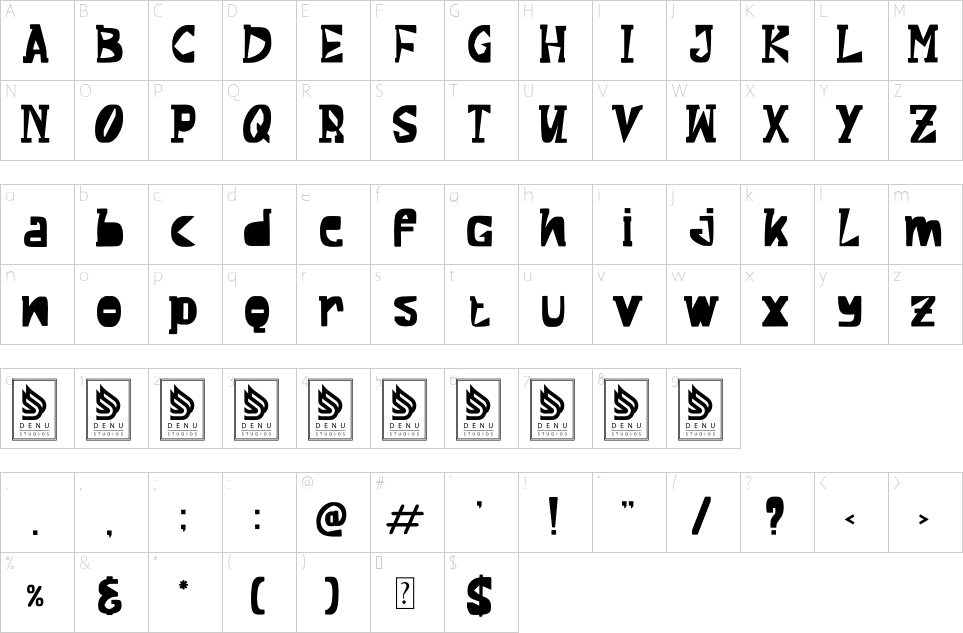
A fonte Munch Mallow é um charmoso adorno para seus designs digitais, projetada pelo designer desconhecido da Gracetypestudio. Se você é um fã de fontes que combinam um toque de modernidade com uma pitada de delicadeza, essa é a fonte para você. Com um design que capta o melhor dos traços de uma fonte cálida e familiar, Munch Mallow é perfeita para nomes de empresas, design gráfico, ou até mesmo para aqueles trabalhos de escritório onde um toque delicado pode transformar a experiência de leitura. Para os designers que buscam uma fonte que combine a facilidade de uso com uma aparência estilosa, Munch Mallow é uma excelente escolha. Seu design arredondado e elegante faz com que seja muito confortável para usar em textos de grande e pequeno tamanho. Não importa se você está fazendo um logotipo inspirado no bebê Munch de “A Pequena Sereia”, criando uma linha de produtos ou apenas redigindo um projeto de escritório, a Munch Mallow estará sempre pronta para dar um toque de criatividade à sua obra. O que mais nos encanta sobre a Munch Mallow é o fato de ser uma fonte gratuita, disponível para Windows e Mac. Isso significa que você pode experimentar o design da fonte sem gastar nada adicional. Com mais de 130 downloads, é evidente que muitos designers já encontraram valor na Munch Mallow e a usaram para expressar sua identidade visual de maneiras únicas e elegantes.